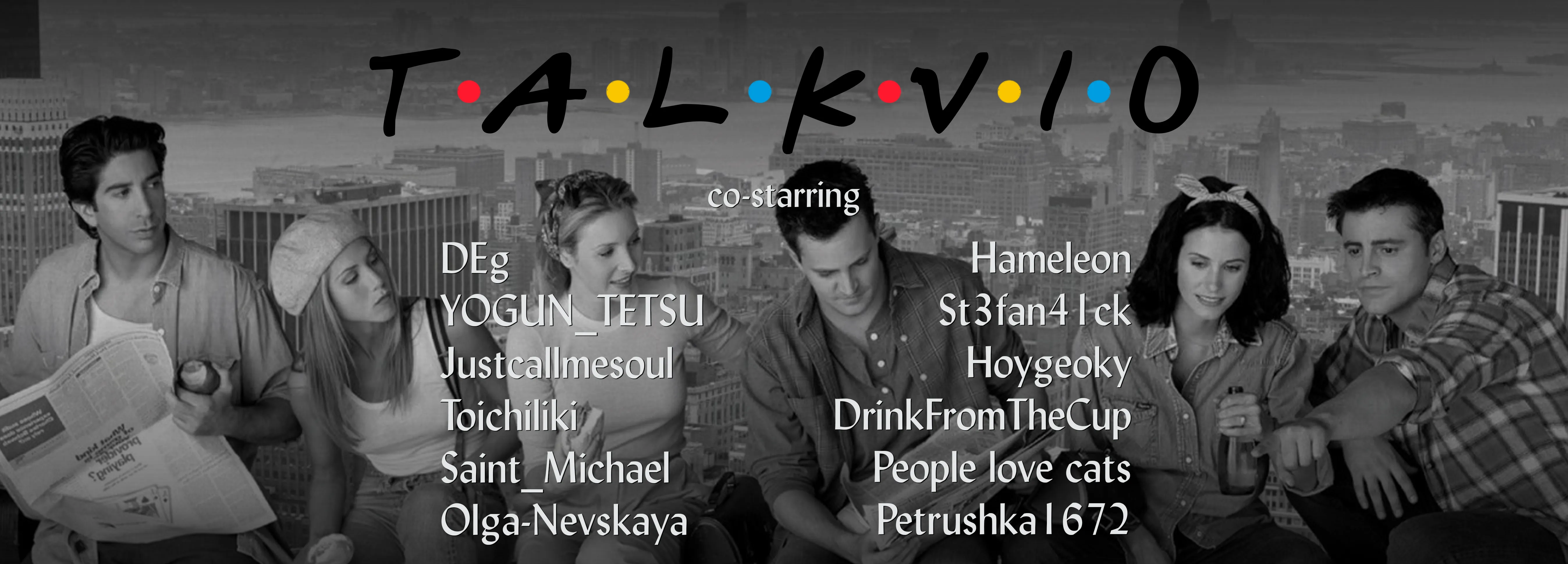
Сегодня тематические «кино-шрифты».
Конечно, ведущий шрифт «Друзей» был сделан специально для сериала. Оригинал найти не получится, но если хотите взять хороший аналог, то сделать это можно тут: ссылка
Но в сериале также есть и доп. шрифт, которым обозначены надписи внутри серий. Для этого создатели использовали интересный шрифт Lydian. Его никак не видоизменяли, лишь наложили лёгкую тень.
Lydian не для коммерции, но зато с кириллицей.
И да, если что, брать лучше первый шрифт из предложенных. Именно он идентичный оригиналу.
Ну так это, наверное, первый шрифт в твоей рубрике с поддержкой кириллицы